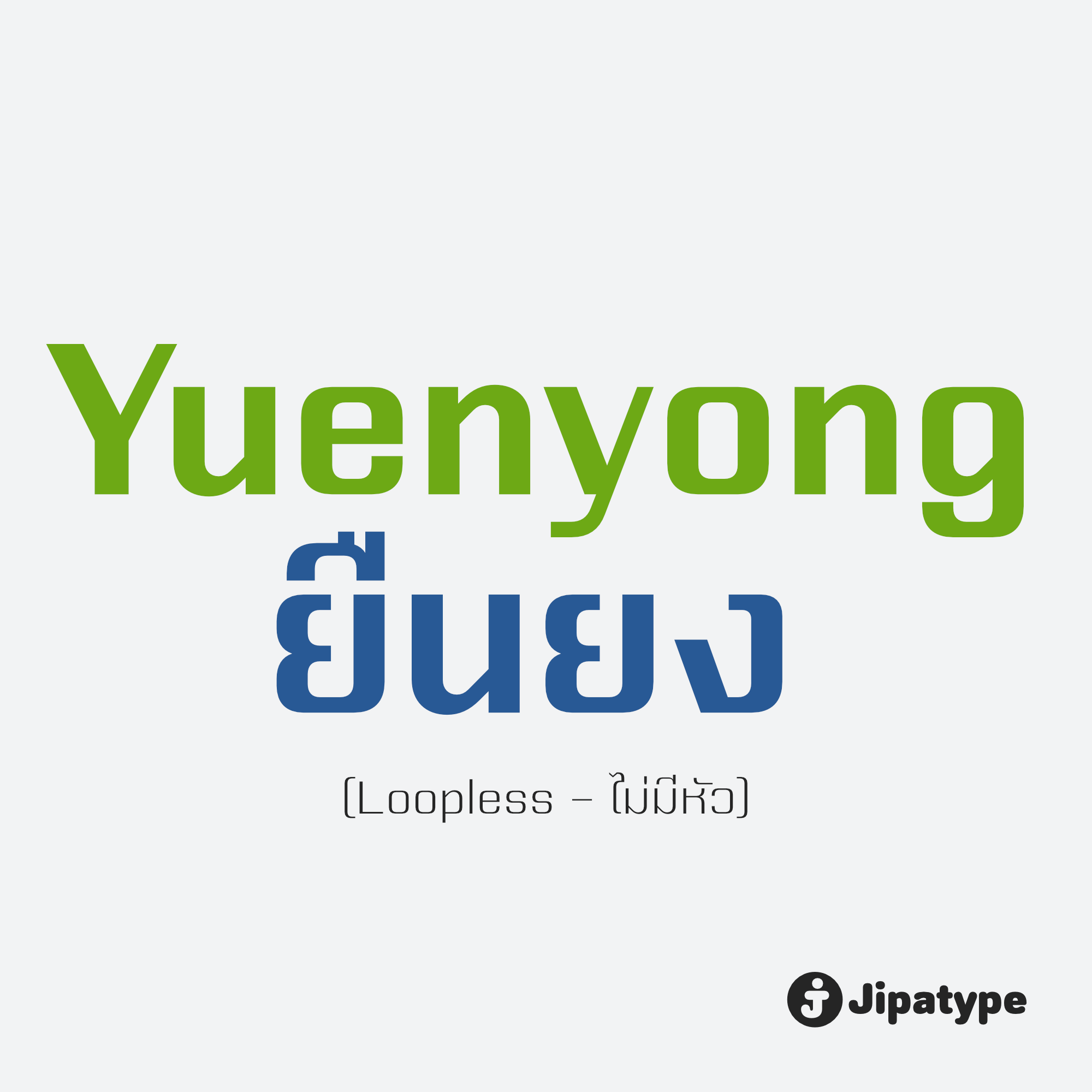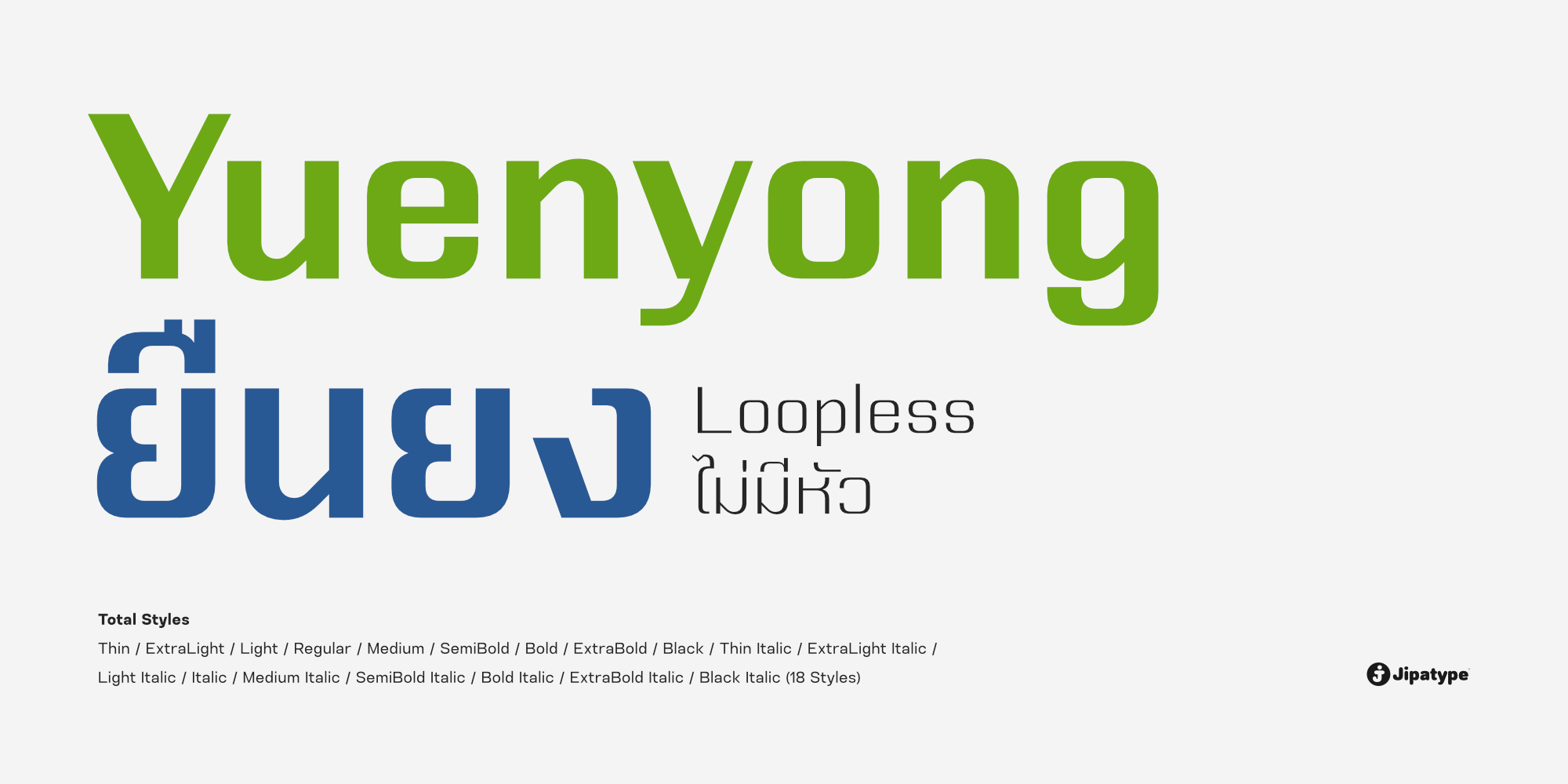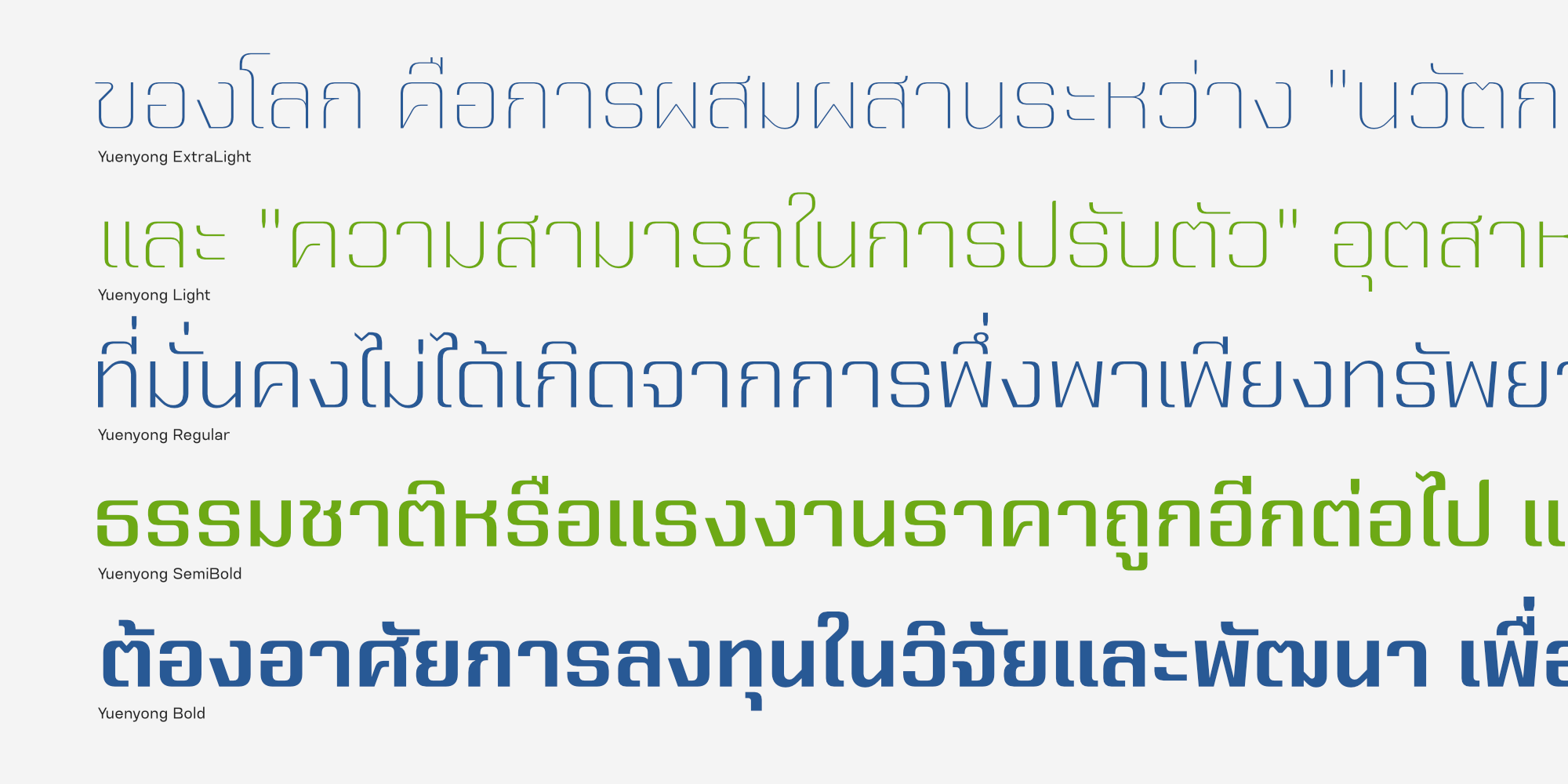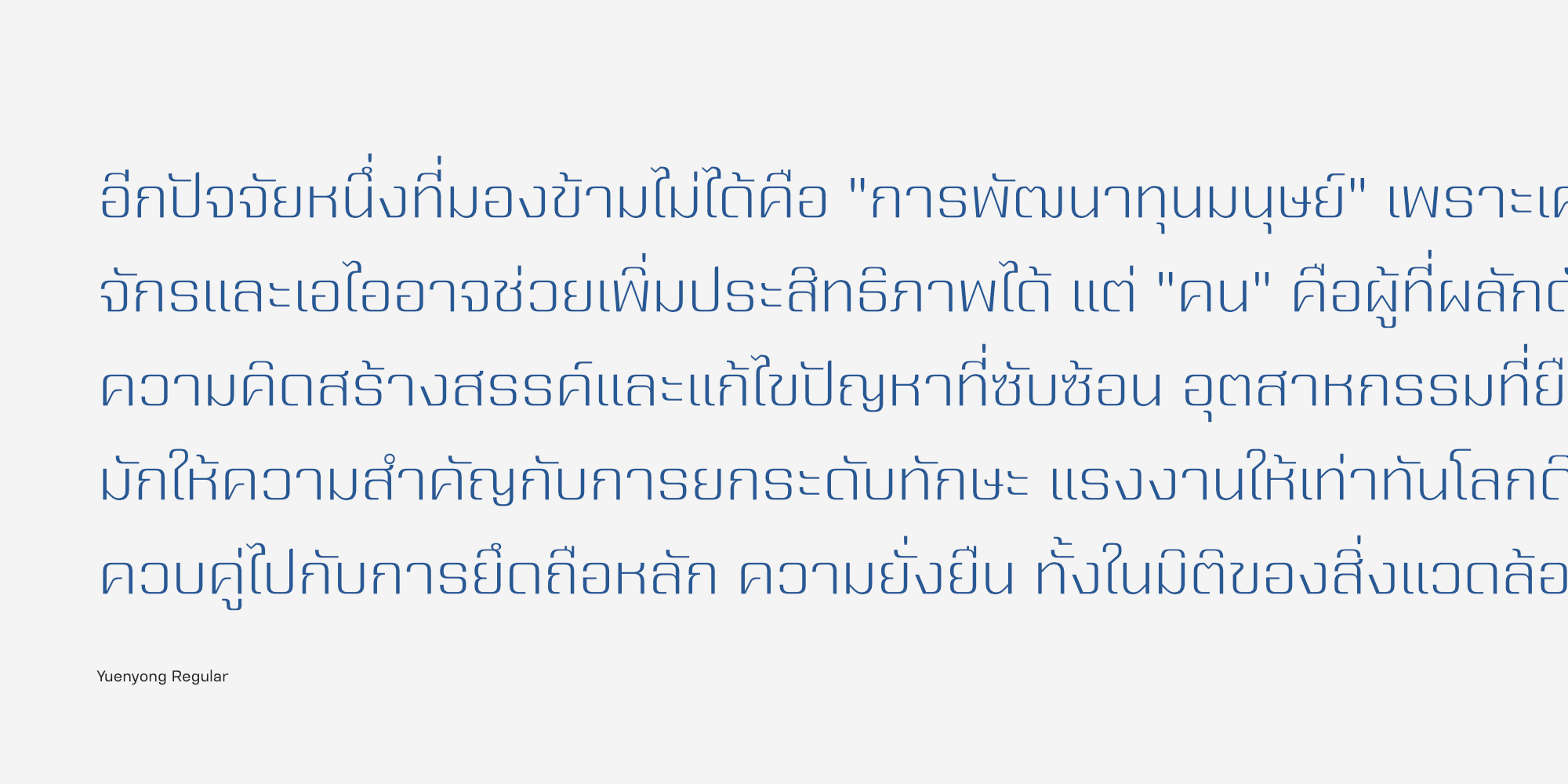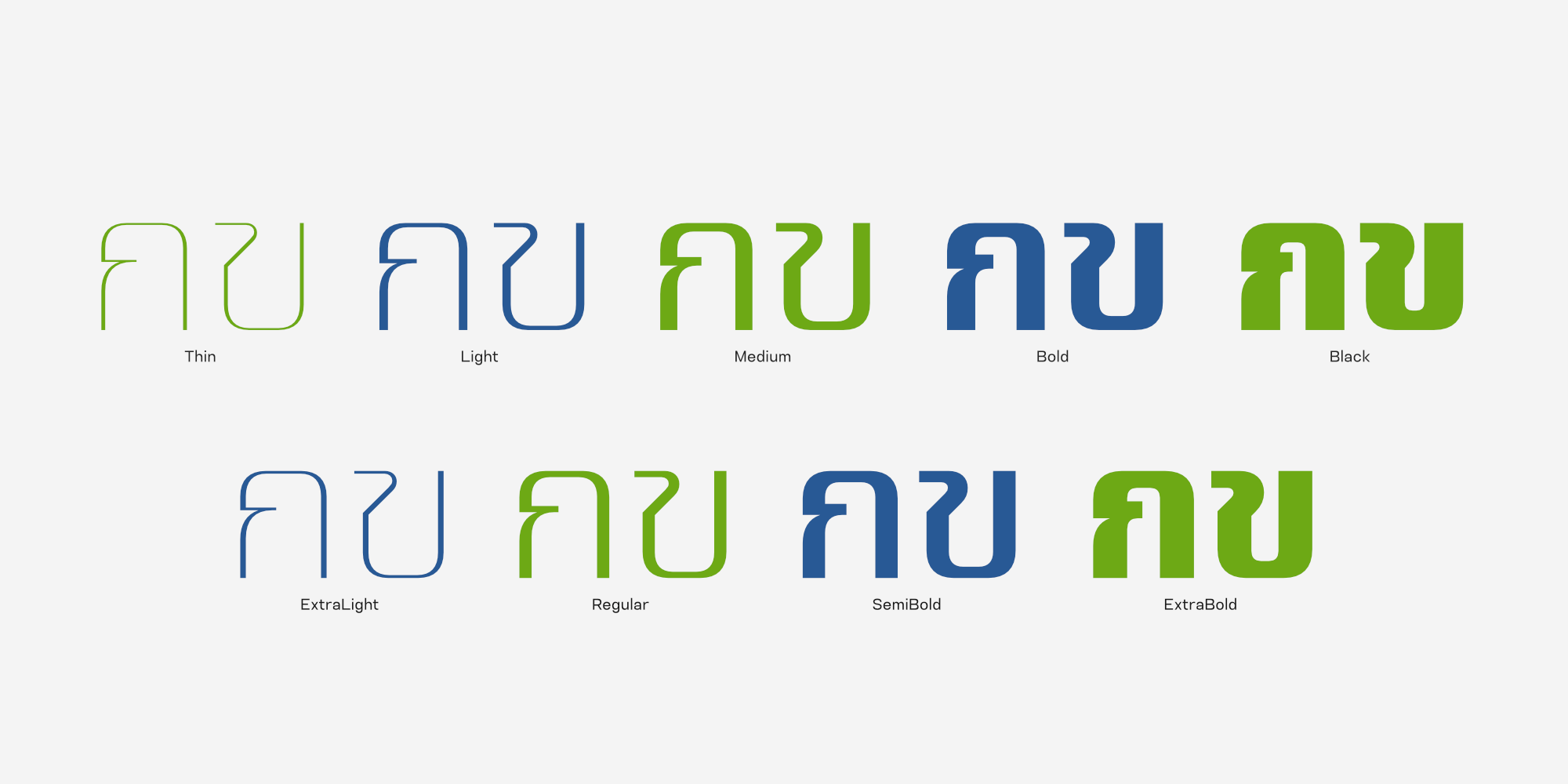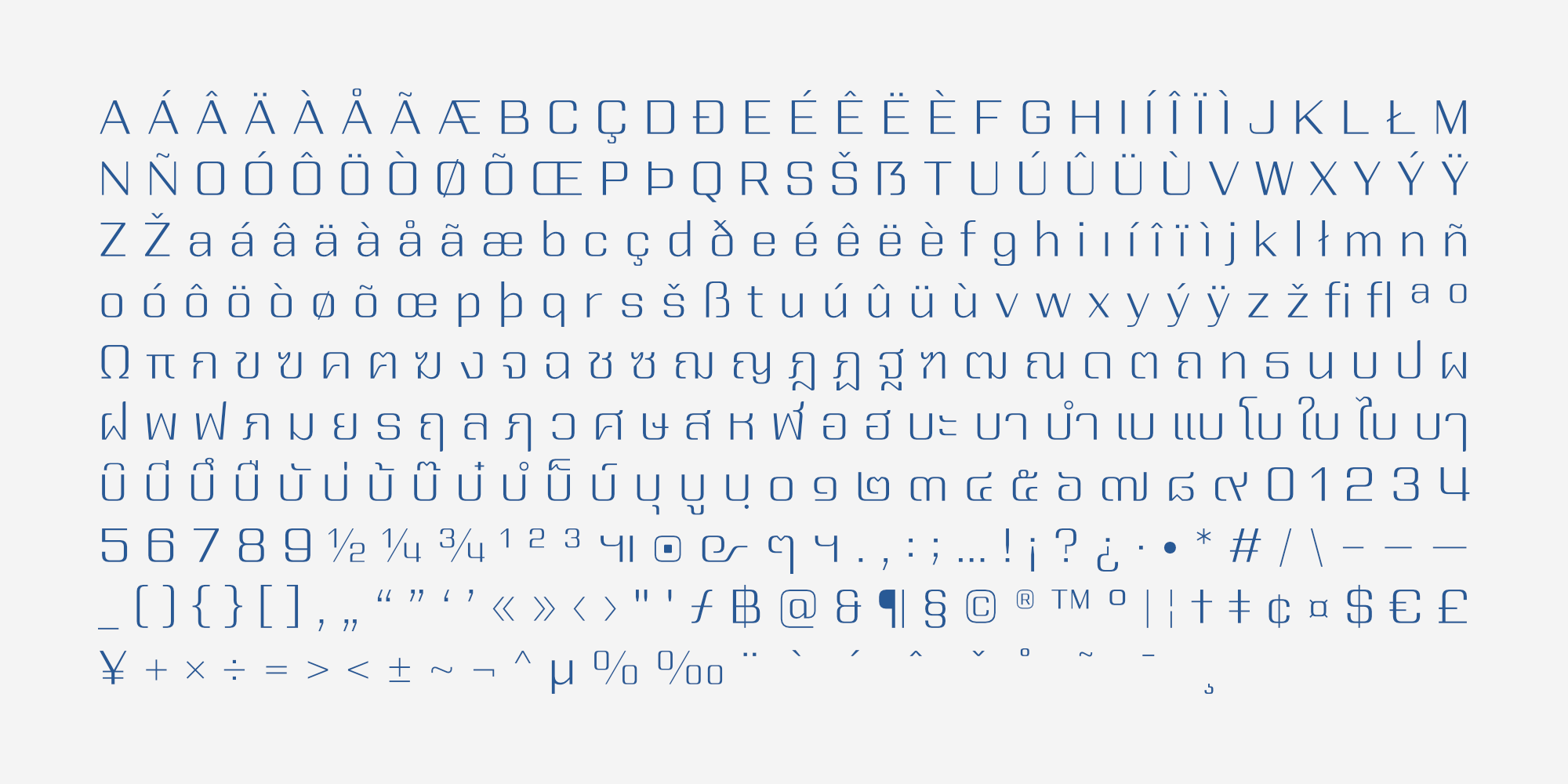
ยืนยง ลูปเลส คือแบบอักษรที่ได้รับการพัฒนาต่อยอดมาจากตระกูล “ยืนยง” (Yuenyong) โดยยังคงรักษาเอกลักษณ์ของโครงสร้างสี่เหลี่ยมมุมมนอันแข็งแรงเอาไว้อย่างครบถ้วน แต่ปรับเปลี่ยนรูปแบบของอักษรไทยให้เป็นแบบ “ไม่มีหัว” (Loopless)
การตัดทอนส่วนหัวเดิมออกไปช่วยลดรายละเอียดที่ซับซ้อนลง ส่งผลให้ตัวอักษรดูโปร่ง โล่ง และมีความเป็นมินิมัล มากยิ่งขึ้น สะท้อนภาพลักษณ์ของความทันสมัยและความคล่องตัวที่เหมาะกับยุคดิจิทัล.
ชุดฟอนต์นี้เหมาะอย่างยิ่งสำหรับแบรนด์ที่ต้องการสื่อสารถึงนวัตกรรม ความก้าวหน้า และวิสัยทัศน์ใหม่ๆ โดยยังคงความน่าเชื่อถือในแบบฉบับของตระกูลยืนยงเอาไว้ มาพร้อมน้ำหนักที่ครบครันถึง 18 สไตล์ ตั้งแต่ตัวบางสุด (Thin) ไปจนถึงตัวหนาสุด (Black) พร้อมตัวเอียง รองรับการใช้งานที่หลากหลายและยืดหยุ่นสำหรับนักออกแบบกราฟิกยุคใหม่.
ออกแบบโดย : อานุภาพ ใจชำนาญ (Anupap Jaichumnan)